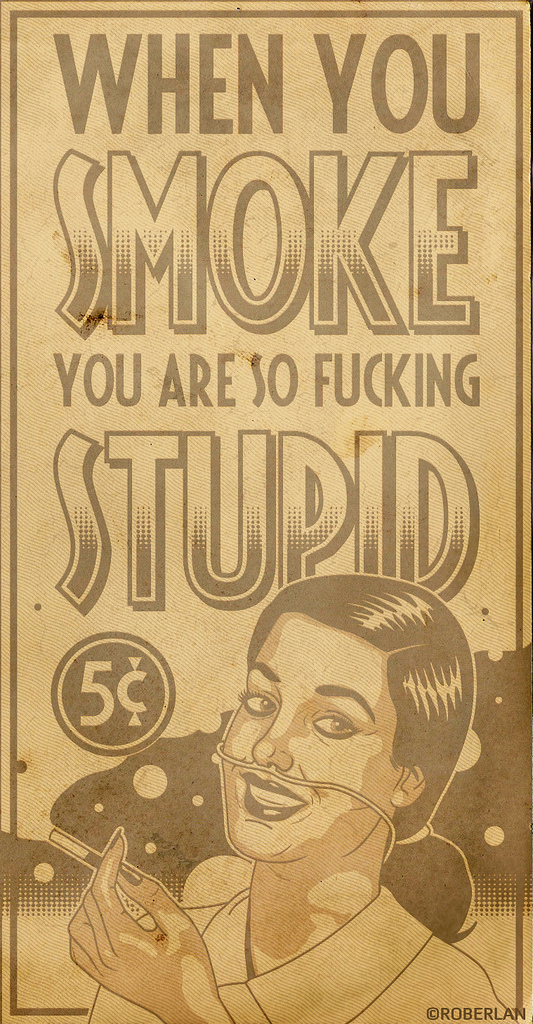
50er Schrift (mit Beispiel)
ich suche diese langgezogene Schrift (besonders am "S" gut erkennbar).
War anscheinend in den 50ern gängig, kenne dies aber auch noch irgendwie aus den 90ern von Technoplatten:
Migrate GD, Oz, Oklahoma … gehen in die Richtung